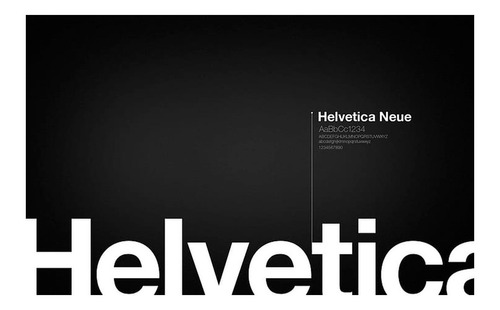
Helvetica (también conocida como Neue Haas Grotesk, Helvetica y últimamente expandida a Neue Helvetica) es una familia tipográfica desarrollada por Max Miedinger conjuntamente con Edouard Hoffmann en 1957 para la fundición de tipografías Haas'sche Schriftgießerei (también conocida como "Haas") de Basilea, Suiza. Su diseño está basado en una anterior tipografía llamada Berthold Akzidenz Grotesk que data de 1896. La tipografía, originalmente llamada Neue Haas Grotesk, es de estilo sencillo y del tipo sans serif o sin remates (Clasif. Vox: Lineale B Neo-Grotesque). Se volvió inmensamente popular a fines de los años 1960 y durante los años 1970, debido a su enorme influencia dentro del llamado "Estilo Tipográfico Internacional" (particularmente en identidades corporativas), una de las más importantes corrientes modernistas del siglo XX.